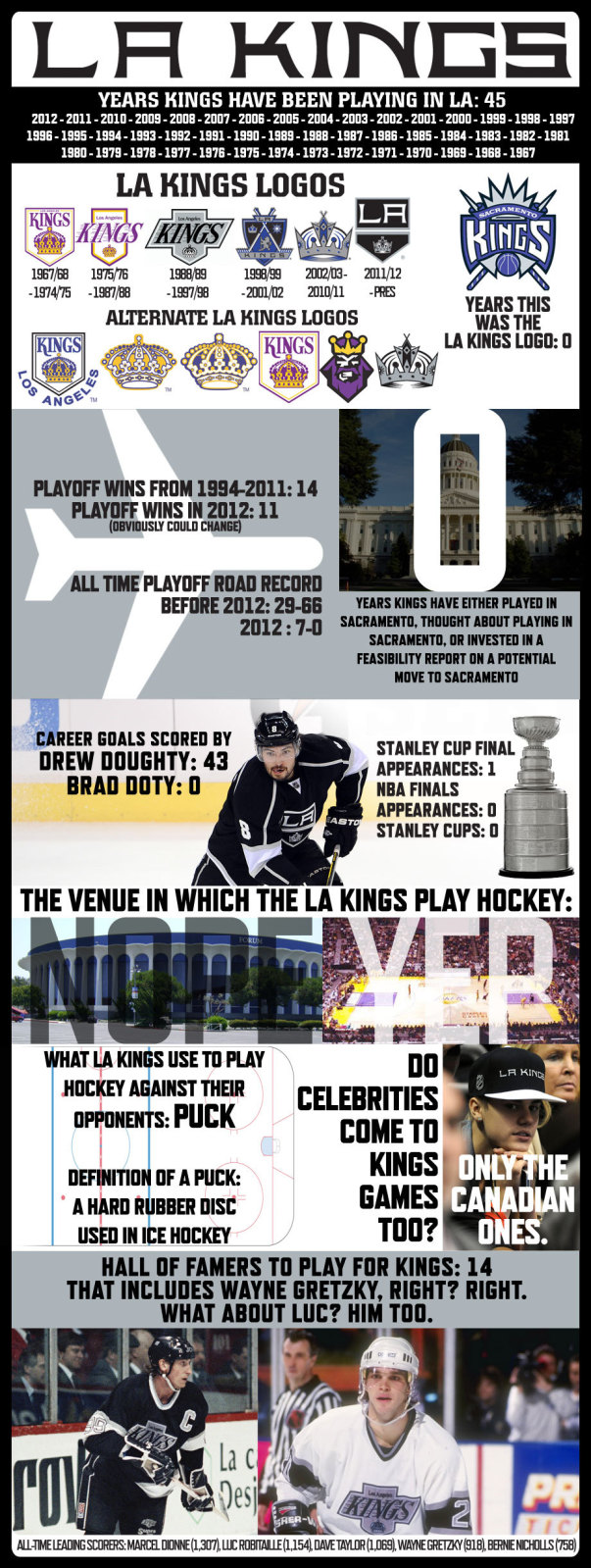
Schriftart für Stickemblem gesucht
ich suche folgende Schriftart, die oft für einen Stick auf Kappen verwendet wird
wäre super wenn jemand weiß um welche Schriftart es sich bei dem Wort "Kings" handelt.
Das ist keine Schriftart, sondern ein (im wahrsten Sinne) selbst gemachter Schriftzug. Leider fehlt es diesem auch an jeglicher Qualität.
Wonder if anyone comes up with an answer; has been looked for on more fora for some time now (all unsolved)
ok, das einzige was ich bisher in die Richtung gefunden habe ist die Economica OT Bold. Leider aber wirklich nur in der Richtung. Wenn das natürlich keine Schriftart ist glaube ich wird es wirklich shcwer. Habe diese Schriftart bzw sehr ähnliche Varianten aber schon mehrmals gesehen, bin mir nicht sicher on alle Nutzer diese dann wirklich selbst zusammengebastelt haben :-/...
… bin mir nicht sicher on alle Nutzer diese dann wirklich selbst zusammengebastelt haben :-/...
Wer ist »alle«? Diese Kappen kommen doch sicher alle von einem Hersteller oder zumindest Lizenzgeber. Und dort wurden diese Schriftzüge dann, wie die anderen schon sagten, »zusammengebastelt«. Das ist eindeutig. Das sind definitiv keine Schriften.
Solche Club-Logos sind zumeist aus einem einfachen Grund speziell gezeichnet. Würde man eine allgemein zugängliche Schriftart benutzen, könnte praktisch jeder irgendwelche Fanartikel auf den Markt bringen,und behaupten, er habe ja nur den Clubnamen in irgend einer Schrift gesetzt, die halt zufällig die gleiche ist, die auch der Club benutzt. So aber ist ein Verstoß gegen die Lizenzbedingungen sofort sichtbar. Für den Verkauf der Fanartikel ist aber auch ein schlechter Entwurf nicht schlimm, da Fans die Fanartikel nicht wegen der Schönheit kaufen, sondern weil sie sich mit dem Club identifizieren.
Das trifft in diesem Fall aber nicht zu, da die gezeigten Mützen dreier verschiedener Mannschaften im gleichen Stil bestickt sind. Mit den CDs dieser Mannschaften hat das Gezeigte nichts zu tun. Es sind halt drei Billig-Mützen.
Solche Club-Logos sind zumeist aus einem einfachen Grund speziell gezeichnet. Würde man eine allgemein zugängliche Schriftart benutzen, könnte praktisch jeder irgendwelche Fanartikel auf den Markt bringen,und behaupten, er habe ja nur den Clubnamen in irgend einer Schrift gesetzt, die halt zufällig die gleiche ist, die auch der Club benutzt. So aber ist ein Verstoß gegen die Lizenzbedingungen sofort sichtbar. Für den Verkauf der Fanartikel ist aber auch ein schlechter Entwurf nicht schlimm, da Fans die Fanartikel nicht wegen der Schönheit kaufen, sondern weil sie sich mit dem Club identifizieren.
Naja, im Prinzip sind die Clubs oder deren Embleme auch nichts anderes als Marken und dann müsste deine Theorie auch auf alle anderen Marken zu treffen  8-)
Einen Schriftzug nachzeichnen ist ja so schwer auch nicht und mit ›zufällig die gleiche Schrift‹ wird man sich auch nicht rausreden können, wenn man logischerweise das Original kennt. Für die Spielernummern mag deine Theorie vielleicht hinkommen, weil die ja auch oft neu gestaltet werden, aber bei Vereinsnamen denke ich eher, dass es da um Eigenständigkeit und Markenbewusstsein geht als um ›Fälschungssicherheit‹.
Ich vermute eine der Stickmaschine eigene Schrift. Der Stick ist qualitativ sehr hochwertig, das lässt auf kein nachträglich erstelltes Stickprogramm schließen, sondern auf die Verwendung einer für den Stick oder sogar für eine spezielle Stickmaschinengattung optimierten Schrift.